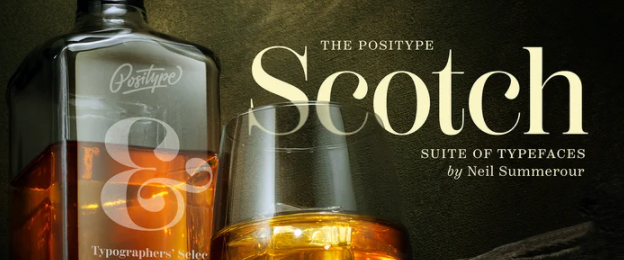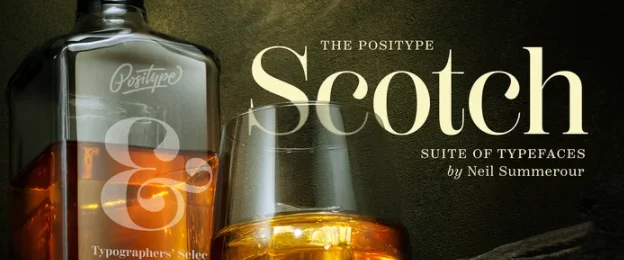
Название: Scotch Font (2021)
Чистый, четкий, рациональный, знакомый, современный... с засечками. Positype Scotch возвращается к истории ровно настолько, чтобы создать что-то теплое и легкое для глаз. Никаких углов, никаких быстрых трюков... этот набор шрифтов был создан для конкретики: Text, Display и Deck... ВСЕ в трех вариантах ширины, которые теперь включают Condensed и Compressed. Каждый уникален, каждый взаимосвязан, каждый является частью целого.
Scotch Text предлагается в 6 вариантах веса с соответствующим истинным курсивом. Начертанные для экономии и легкого чтения, эти семейства являются рабочей лошадкой для работы с длинными текстами. 4 набора цифр, хорошо пропорциональные маленькие прописные буквы и множество дополнительных элементов дополняют каждый шрифт.
Scotch Display - это не просто более тонкая версия Scotch Text с более высоким контрастом. В Display более короткие восходящие и нисходящие линии, уникальное начертание, великолепный контраст и более складчатый, каллиграфический курсив. Display тонко источает изысканность и является привлекательным, буйным компаньоном Scotch Text.
Scotch Deck завершает предложение, предпочитая быть специфичным для своего предложения. Deck использует черты и пропорции, общие для Text и Display, но изменяет общую массу, чтобы сбалансировать потребности в настройках, требующих подзаголовков, призывов и других подобных применений. По сути, это что-то не очень высококонтрастное и не очень напряженное, что отлично подходит для средних размеров.